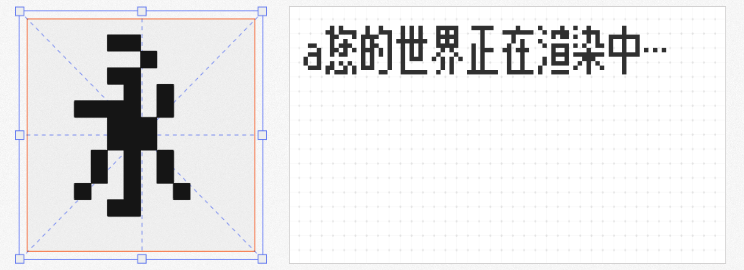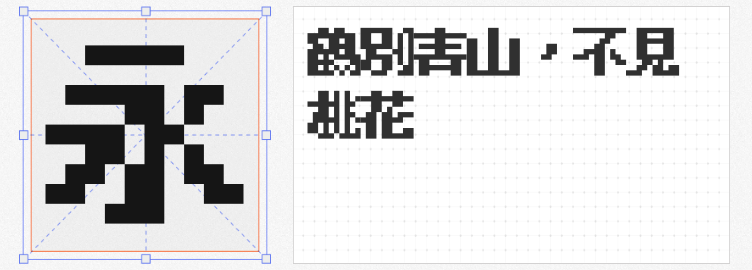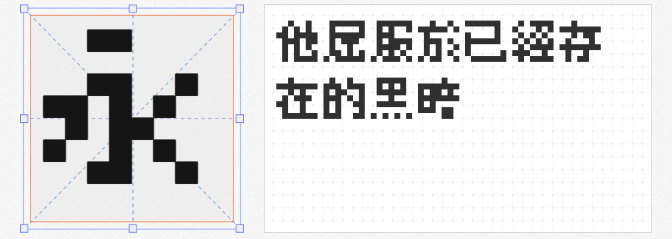
在像素艺术复兴的浪潮中,字体作为构建游戏世界观的关键元素,既要承载复古情怀,又需兼顾现代设计的可读性与扩展性。本文精选四款开源免费、专为像素场景优化的中文字体,从风格特征到应用场景进行深度解析,助力开发者低成本打造高辨识度的游戏视觉体系。
以经典FC游戏字体为蓝本,通过融合M+ BITMAP FONTS与ベストテン(BestTen-DOT)的基因,打造出极具8-bit风格的繁体中文解决方案。其9×9像素网格精准复刻早期游戏机的显示特性,针对"辶""阝"等复杂部首进行像素密度优化,确保在16px以下尺寸仍保持清晰轮廓。
2. 目哉像素体 Orig
基于k8x12字体重构的8×12中日文像素字体,采用模块化设计实现跨语言视觉统一。所有笔画严格遵循像素网格对齐原则,通过重构"口""日"等封闭结构的内部像素分布,在极小字号下依然维持高识别度。
3. 精品点阵体7×7
作为美咲フォント的像素化变体,以7×7超小网格挑战中文显示极限。通过合并"纟""讠"等偏旁的共享像素,在56个像素点内完整呈现汉字结构。其动态模糊补偿技术可有效解决高速滚动时的文字闪烁问题,特别适用于弹幕射击游戏与像素风股市模拟器等需要密集显示信息的场景。
作为开源泛中日韩像素字体,以黑体无衬线风格重新定义像素字体规范。严格遵循《通用规范汉字表》的字形标准,消除"吕""冒"等易错字的歧义设计。该字体支持中日韩统一表意文字扩展B区,是开放世界像素游戏与教育类编程模拟器的标准化选择。